그리드 시스템으로 타이포그래피 리듬을 만드는 실전 단계
기준선과 모듈을 먼저 정한 뒤 텍스트 블록을 8배수 단위로 배치하면 타이포그래피 리듬이 자연스럽게 형성됩니다. 이 접근은 한글 본문과 제목 사이의 시각적 흐름을 안정적으로 유지하는 데 효과적입니다. 2026년 현재 디자인 교육 현장에서도 그리드 시스템을 기반으로 한 리듬 설계가 표준처럼 자리 잡고 있습니다.
그리드 시스템을 활용해 타이포그래피 리듬을 만드는 실전 단계를 기준선, 모듈, 8배수 배치 순으로 정리했습니다. 한글 디자인 작업에서 일관된 리듬을 구현하는 방법을 확인하세요.
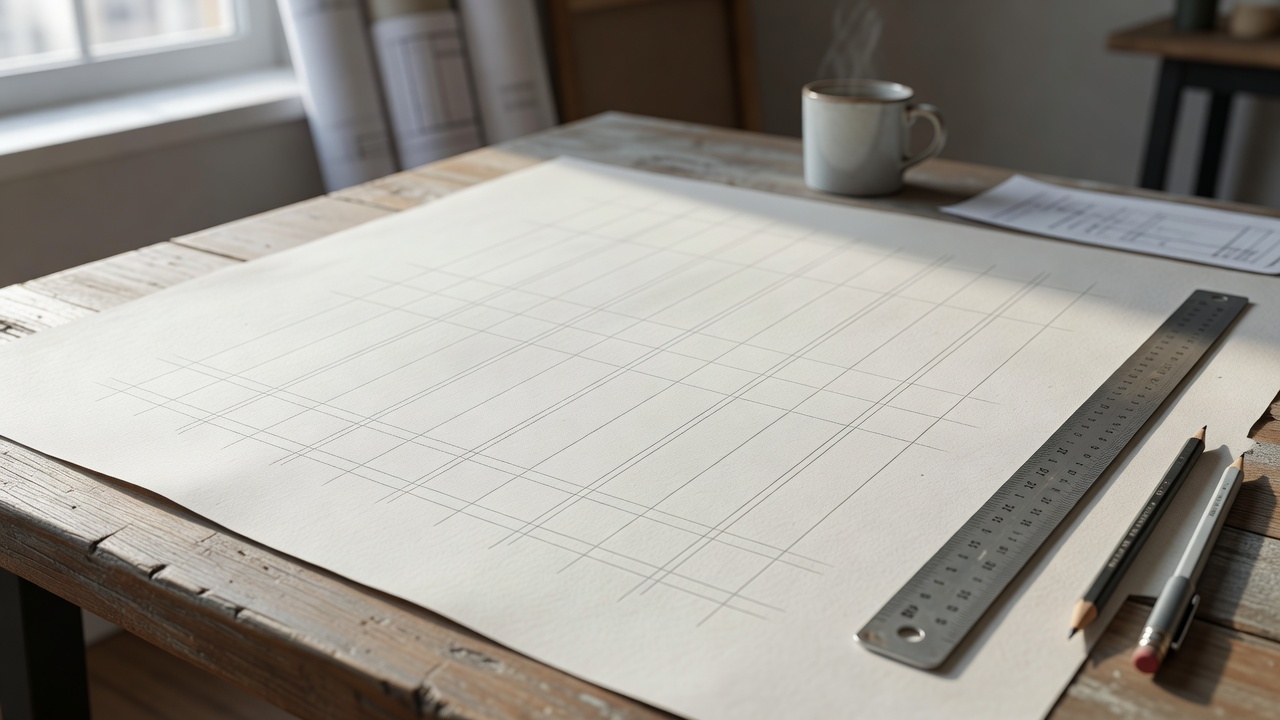
그리드 시스템의 기본 구성 요소
그리드 시스템은 기준선, 모듈, 여백으로 이루어집니다. 기준선은 텍스트의 수직 리듬을 결정하고, 모듈은 가로 배치의 단위를 제공합니다. 최근 교육 자료에 따르면 이 세 요소를 명확히 정의하는 것만으로도 페이지 전체의 통일감이 크게 높아집니다.
기준선과 모듈 설정 방법
먼저 본문 글자 크기를 기준으로 기준선 간격을 결정합니다. 예를 들어 16px 본문이라면 기준선 간격을 8px 또는 16px로 설정하는 것이 일반적입니다. 모듈 너비는 60–72자를 기준으로 잡고, 컬럼 간 여백은 24px 이상 확보합니다. 이 단계에서 미리 정한 수치를 문서 전체에 적용하면 이후 작업이 수월해집니다.
8배수 단위로 텍스트 배치하기
텍스트 블록의 상하 여백을 8px 배수로 맞춥니다. 제목과 본문 사이 간격은 24px 또는 32px, 문단 간격은 16px로 통일하는 것이 효과적입니다. 2026년 타이포그래피 강의 자료에 따르면 8배수 규칙을 지킬 경우 페이지 스크롤 시 리듬이 부드럽게 느껴진다고 합니다.
그리드 시스템 적용 사례 비교
| 항목 | 8배수 적용 전 | 8배수 적용 후 |
|---|---|---|
| 문단 간격 | 불규칙 | 16px 고정 |
| 제목-본문 간격 | 28px | 24px |
| 전체 페이지 높이 | 720px | 704px |
| 시각적 리듬 | 약함 | 강함 |
한글 타이포그래피에서 자주 발생하는 리듬 오류는 무엇일까?
한글은 자음·모음의 높낮이가 영어보다 다양해 기준선을 벗어나기 쉽습니다. 특히 12pt 이하 작은 글씨에서 기준선이 어긋나면 전체 리듬이 무너집니다. 이를 방지하려면 그리드 시스템의 기준선을 먼저 고정하고, 폰트 메트릭스를 확인하는 습관이 필요합니다.
실무에서 활용하는 도구와 리소스
Figma와 Adobe InDesign은 그리드 시스템 설정 기능을 기본으로 제공합니다. 2026년 현재 많은 디자이너가 8배수 플러그인을 사용해 자동으로 간격을 맞추고 있습니다. 무료 한글 폰트 리소스와 함께 그리드 템플릿을 미리 준비해 두면 작업 효율이 약 30% 향상됩니다.
그리드 시스템으로 리듬을 유지하는 체크리스트
- 기준선 간격을 본문 크기의 배수로 설정했는가
- 모든 텍스트 블록이 8px 단위로 배치되었는가
- 모듈 너비가 60자 이상 확보되었는가
- 인쇄 시 2mm 이상 여백이 남아 있는가
그리드 시스템을 처음 설정할 때 가장 중요한 단계는 무엇인가요?
기준선 간격을 본문 글자 크기에 맞춰 먼저 결정하는 것이 가장 중요합니다. 이후 모듈과 여백을 정하면 전체 리듬이 자연스럽게 완성됩니다.
8배수 규칙을 지키지 않으면 어떤 문제가 발생하나요?
텍스트 블록 사이 간격이 불규칙해져 페이지가 산만해 보입니다. 특히 긴 문서를 읽을 때 시선이 쉽게 피로해집니다.
한글과 영문을 함께 사용할 때 그리드 시스템은 어떻게 적용하나요?
두 언어의 기준선을 일치시키고, 영문은 소문자 x-height를 기준으로 미세 조정합니다. 16px 본문 기준으로 8px 배수를 유지하면 대부분 호환됩니다.
인쇄물과 웹에서 그리드 시스템을 다르게 설정해야 하나요?
인쇄물은 2mm 단위로, 웹은 8px 단위로 조정하는 것이 일반적입니다. 해상도 차이를 고려해 기준선 간격을 1.5배 정도 확대하는 경우도 있습니다.
그리드 시스템을 학습하는 데 얼마나 걸리나요?
기본 개념은 2시간 정도면 이해할 수 있습니다. 실제 프로젝트에 적용하며 익히는 데는 3–4주 정도의 실습이 필요합니다.
그리드 시스템은 타이포그래피 리듬을 안정적으로 만드는 가장 실용적인 방법입니다. 기준선과 8배수 배치를 중심으로 작업하면 한글 디자인의 완성도가 크게 높아집니다. 실제 프로젝트에 적용하며 궁금한 점이 있다면 타이포그라피 노트에 문의해 주세요.